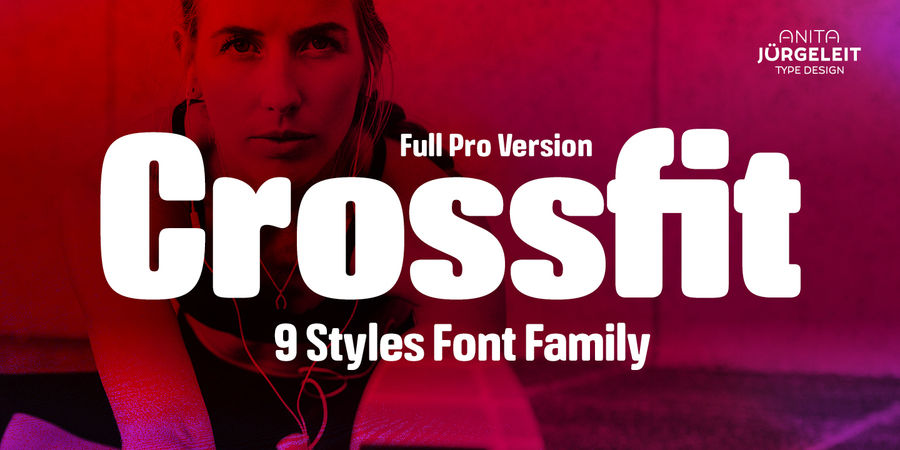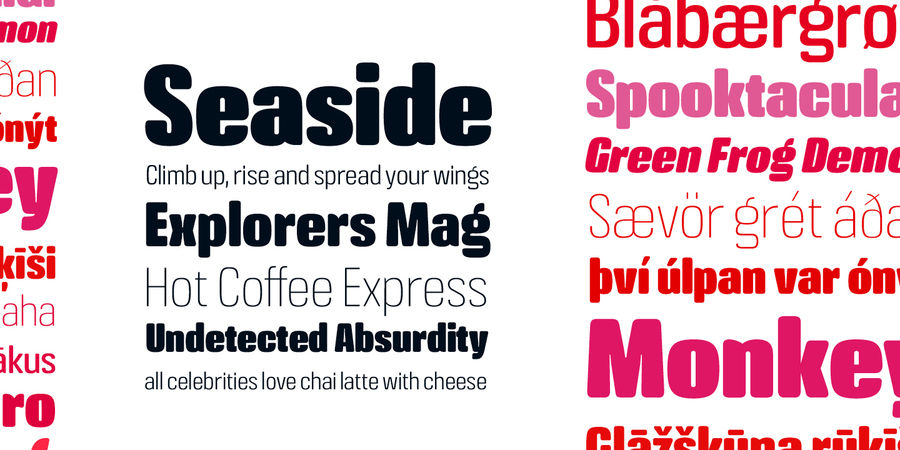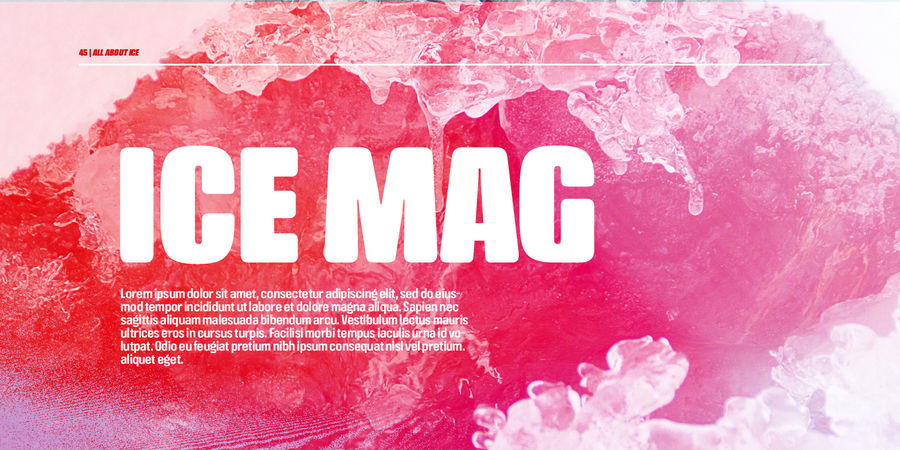
Опис гарнітури Crossfit – це нове сімейство шрифтів для заголовків. Ідеально для набору текстів великим кеглем. Наприклад, великих кіноафіш, рекламних або редакційних заголовків. Він може підійти таким темам: спорт, пригоди, сувора природа і найрізноманітніші складні життєві ситуації. Його сміливість і стабільність перетворить ваш твір в дизайн, якість якого не підлягає сумніву. Crossfit сміливий, чистий і в той же час доброзичливий, завдяки заокругленості кутів.
Шрифтове сімейство Crossfit містить 9 накреслень у 8 варіантах насиченості: hairline, thin, light, roman, demi, bold, black, heavy.
OpenType функції: sub і superscript, nominators і denominators, fractions, ordinals.
Шрифтове сімейство Crossfit підтримує 90 мов, у яких використовуються латинські символи.
Шрифт розробила Аніта Юргелейт у 2019 році.
Асоціації з сімейством шрифтів CrossfitОсобистість і характер гарнітури:
неоновий, рівний, статичний, легкий, міський, сучасний, урбаністичний, прозорий, спокійний, дротяний, якісний, стрункий, худий, економний, стійкий, чіткий, стабільний, серйозний, практичний, технічний, міцний, надійний, спортивний, комфортний, здоровий, стриманий, добрий, акуратний, сильний, мирний, переконливий, впевнений, крутий, амбітний, гучний, важливий, суворий, важкий, гарячий, гумовий, М'який, гладенький, надувний, соковитий, мотивуючий, універсальний, гнучкий, теплий, чистий, помітний, тісний, щільний, потужний, мужній, значний, авторитетний, наполегливий, відповідальний, промисловий, сміливий, строковий